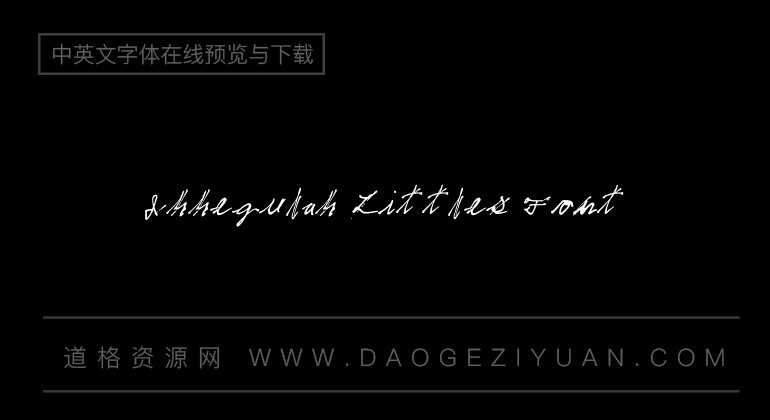
Irregular Littles是一种手写风格的不规则字体,其特点是字母形状不规则、笔画粗细不一、倾斜、有些字母甚至是不连通的。这种字体通常被用于设计海报、印刷品、广告等艺术设计领域,因为它可以带来一种有趣、自然、非正式的视觉效果。 Irregular Littles字体在表现力和独特性方面具有很高的优势。它适用于许多不同的设计场景,如手写字体、品牌标志、包装设计等。此外,Irregular Littles还具有很好的可读性,尤其是在大号字体的情况下。 总之,Irregular Littles是一种充满个性的字体,它有很多用途,可以为你的设计作品带来独特的视觉效果。内容介绍
Irregular Littles Font是一款非常不错的手写艺术字体,具有很好的视觉感,适合于文化类的宣传设计、商业类品牌的广告和产品包装设计以及个性化文字排版等较多场景。